유명 브랜드의 로고는 간결하면서도 강한 인상을 남기는 디자인의 정석이예요. 싸인도 브랜드 로고처럼 단순하면서도 기억에 남고, 개성이 돋보이도록 만들어야 해요. ✍🔥
내가 생각했을 때, 브랜드 로고 디자인 원리를 싸인에 적용하면 더 세련되고 멋진 스타일을 완성할 수 있어요. 이제 싸인 디자인에 활용할 수 있는 유명 브랜드 로고의 특징을 알아볼까요? 🚀
브랜드 로고와 싸인의 공통점 🎨
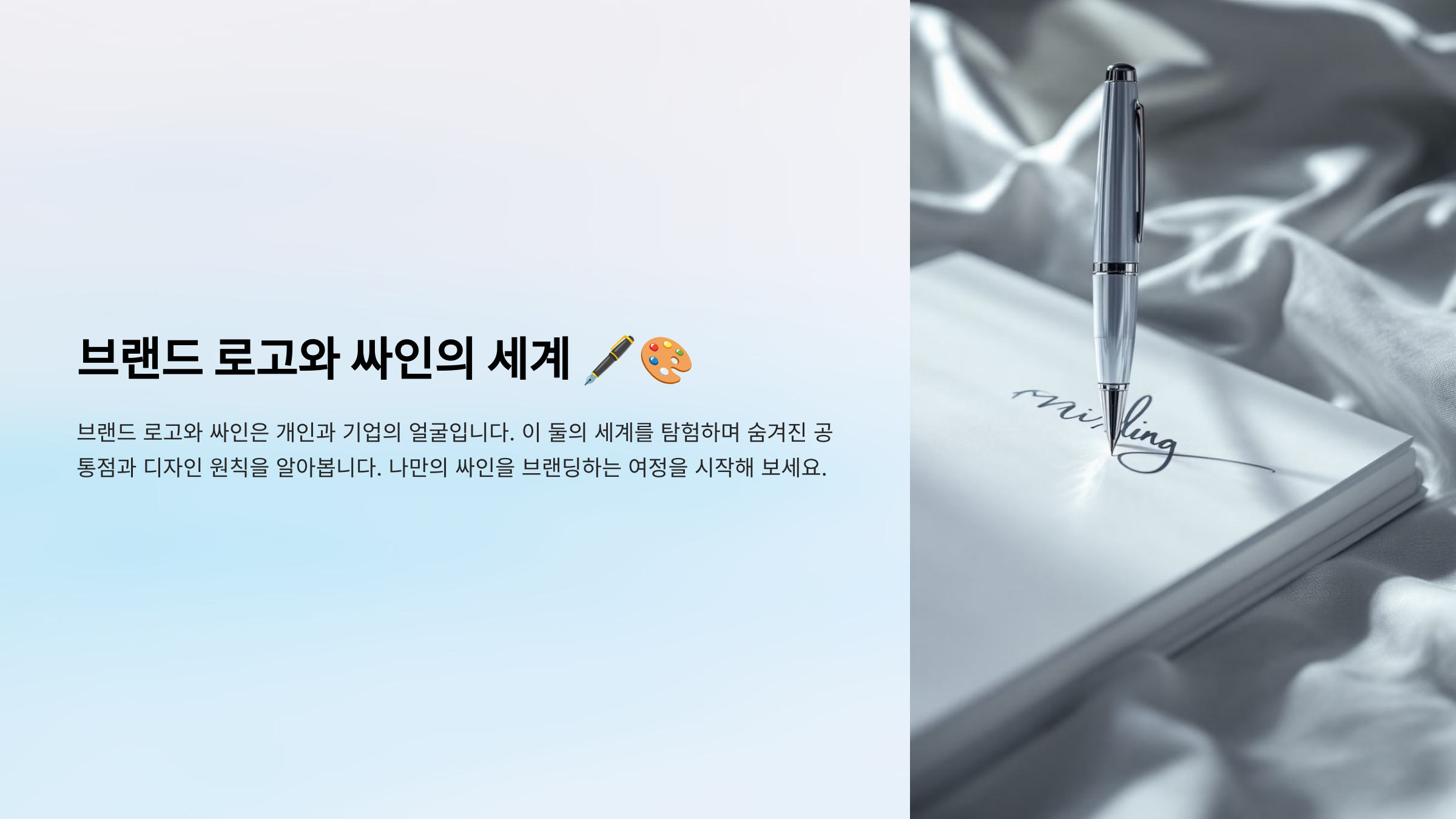
싸인과 브랜드 로고는 단순한 글자가 아니라 강한 인상을 남기는 디자인 요소예요. 브랜드 로고가 회사의 정체성을 나타내듯, 싸인도 자신만의 개성을 드러내는 중요한 요소랍니다! ✍🔥
🔹 브랜드 로고와 싸인의 공통점
✔ 한 번 보면 기억에 남아야 한다
✔ 너무 복잡하지 않고 간결해야 한다
✔ 디자인의 흐름과 균형이 중요하다
✔ 개성을 반영해야 브랜드(싸인)의 차별성이 생긴다.
📌 브랜드 로고 & 싸인의 유사점 ✨
비교 요소 브랜드 로고 개인 싸인 기억에 남는 디자인 아이콘이나 심볼을 사용해 인상적인 로고 제작 이니셜 강조 또는 독특한 필기체 활용 간결함 불필요한 장식을 줄이고 단순한 형태 유지 빠르게 쓸 수 있도록 복잡한 요소 제거 개성 표현 브랜드의 정체성을 색상과 폰트로 표현 이름의 특성을 살려 개성 있게 디자인 균형과 흐름 로고의 크기와 간격을 정리해 균형 유지 획의 연결과 마무리를 부드럽게 조정 이제 심플하지만 강렬한 브랜드 로고의 특징을 살펴볼까요? 🔥
심플하지만 강렬한 브랜드 로고 특징 🔥
유명 브랜드의 로고를 보면 단순하면서도 강한 인상을 남기는 특징이 있어요. 싸인도 마찬가지로 불필요한 요소를 줄이고, 기억에 남는 디자인을 만들어야 해요. ✍🔥
🔹 강렬한 브랜드 로고의 특징
✔ 단순한 디자인 – 복잡한 요소 없이 깔끔한 형태
✔ 한눈에 알아볼 수 있는 구조 – 직관적인 스타일
✔ 균형 잡힌 비율 – 너무 길거나 짧지 않게 조정
✔ 특징적인 포인트가 있음 – 로고만 보고도 브랜드를 떠올릴 수 있음
📌 유명 브랜드 로고에서 배우는 핵심 ✨
브랜드 로고 특징 싸인에 적용 가능? Nike 곡선의 스우시(swoosh) 심볼, 빠르고 역동적인 느낌 싸인의 끝을 부드러운 곡선으로 마무리 Coca-Cola 부드러운 필기체 스타일, 유려한 곡선 싸인을 필기체로 자연스럽게 연결 Apple 심플한 아이콘, 불필요한 요소 없음 싸인을 최소한의 획으로 구성 Google 밝고 친근한 색상, 명확한 가독성 싸인을 명확하고 직관적으로 디자인 이제 유명 브랜드에서 배우는 싸인 디자인 원칙을 알아볼까요? ✅
유명 브랜드에서 배우는 싸인 디자인 원칙 ✅
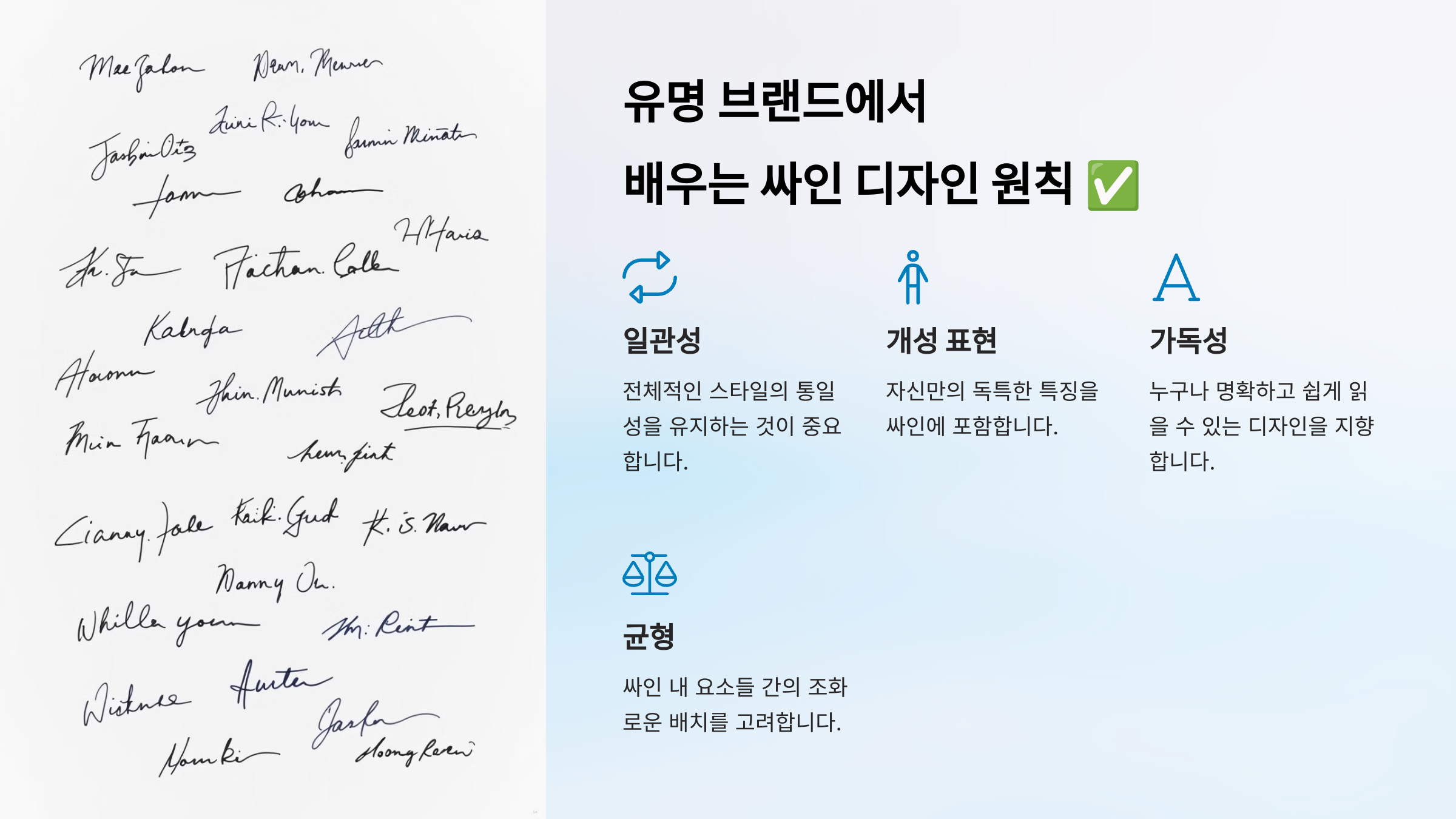
브랜드 로고처럼 싸인도 단순하면서도 강렬한 인상을 남겨야 해요. 유명 브랜드의 디자인 원칙을 참고하면 더욱 세련되고 기억에 남는 싸인을 만들 수 있어요! ✍🔥
🔹 싸인 디자인 원칙 4가지
✔ 미니멀리즘 – 불필요한 요소를 제거하고 핵심만 남기기
✔ 균형과 조화 – 글자의 크기와 간격을 조정해 안정감 있는 디자인 만들기
✔ 흐름과 속도 – 자연스럽게 이어지는 획을 활용해 부드러운 스타일 완성
✔ 차별화된 개성 – 이니셜, 곡선, 밑줄 등 자신만의 특징을 추가
📌 싸인 디자인 원칙 4가지 ✨
원칙 설명 예시 미니멀리즘 복잡한 장식을 줄이고 심플한 스타일 유지 Apple 로고처럼 간결한 싸인 균형과 조화 글자의 크기, 간격, 기울기를 맞춰 정돈된 디자인 Google 로고처럼 가독성이 좋은 싸인 흐름과 속도 자연스럽게 이어지는 획으로 부드러운 필기체 구성 Coca-Cola 로고처럼 유려한 곡선 활용 차별화된 개성 이니셜, 독특한 기호, 밑줄 등을 활용해 브랜드화 Nike 로고처럼 독창적인 포인트 추가 이제 브랜드 로고에서 따온 싸인 스타일 예시를 살펴볼까요? ✍
브랜드 로고에서 따온 싸인 스타일 예시 ✍
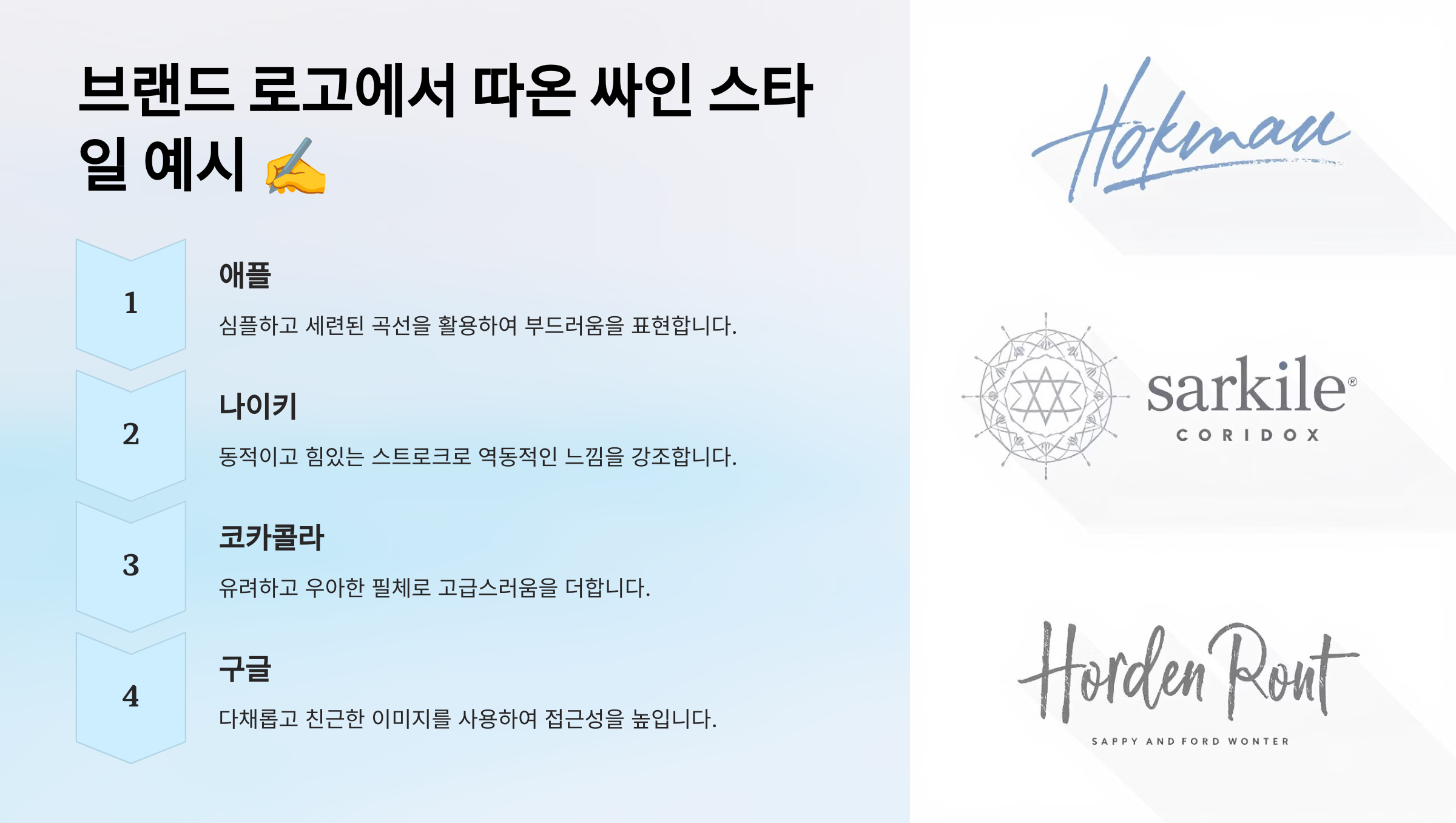
유명 브랜드의 로고를 참고하면 더 세련되고 강렬한 싸인을 만들 수 있어요. 각 브랜드가 가지고 있는 디자인 원리를 싸인에 적용하면 독창적인 스타일을 완성할 수 있답니다! ✍🔥
🔹 브랜드에서 영감 얻은 싸인 스타일
✔ Nike 스타일 – 곡선을 활용한 빠르고 유려한 흐름
✔ Coca-Cola 스타일 – 필기체를 부드럽게 연결해 감각적인 느낌
✔ Apple 스타일 – 군더더기 없이 심플한 디자인
✔ Lacoste 스타일 – 이니셜과 작은 심볼을 활용한 개성적인 스타일
📌 브랜드 로고 기반 싸인 스타일 예시 ✨
브랜드 스타일 싸인 적용 방식 특징 Nike 곡선을 강조하여 역동적인 느낌 부드러운 흐름, 빠른 필기 가능 Coca-Cola 필기체를 활용해 자연스럽게 연결 우아하고 감각적인 스타일 Apple 불필요한 요소 없이 간결하게 구성 미니멀하면서도 세련된 느낌 Lacoste 이니셜과 작은 기호를 조합 독창적인 포인트 추가 가능 이제 싸인에 적용할 수 있는 디자인 요소를 살펴볼까요? 🎯
싸인에 적용할 수 있는 디자인 요소 🎯
싸인을 더욱 세련되게 만들려면 디자인 요소를 적절히 활용하는 것이 중요해요. 단순한 글씨를 넘어, 브랜드 로고처럼 시각적으로도 매력적인 스타일을 만들어야 해요! ✍🔥
🔹 싸인에 활용할 수 있는 디자인 요소
✔ 곡선과 직선 조화 – 부드러운 흐름을 살리거나 강한 인상을 주는 요소
✔ 이니셜 강조 – 싸인의 첫 글자를 키우거나 특이한 획 추가
✔ 밑줄 및 기호 추가 – 별⭐, 점•, 스마일😊 등 개성 있는 포인트
✔ 대문자 & 소문자 조합 – 글자 크기 변화를 통해 스타일 살리기
📌 싸인 디자인에 활용할 요소 ✨
디자인 요소 설명 활용 예시 곡선과 직선 조화 부드러운 곡선과 강한 직선 조합으로 인상적 디자인 Nike 스타일의 유려한 흐름 이니셜 강조 첫 글자를 키우거나 특이한 획 추가 Tesla CEO 엘론 머스크 스타일 밑줄 및 기호 추가 밑줄, 점, 작은 기호 등을 활용해 개성 표현 Lacoste 로고처럼 작은 기호 활용 대문자 & 소문자 조합 글자의 크기를 변형해 스타일 연출 Coca-Cola의 필기체 조합 이제 브랜드처럼 나만의 싸인 브랜딩하는 법을 알아볼까요? 💼
브랜드처럼 나만의 싸인 브랜딩하기 💼
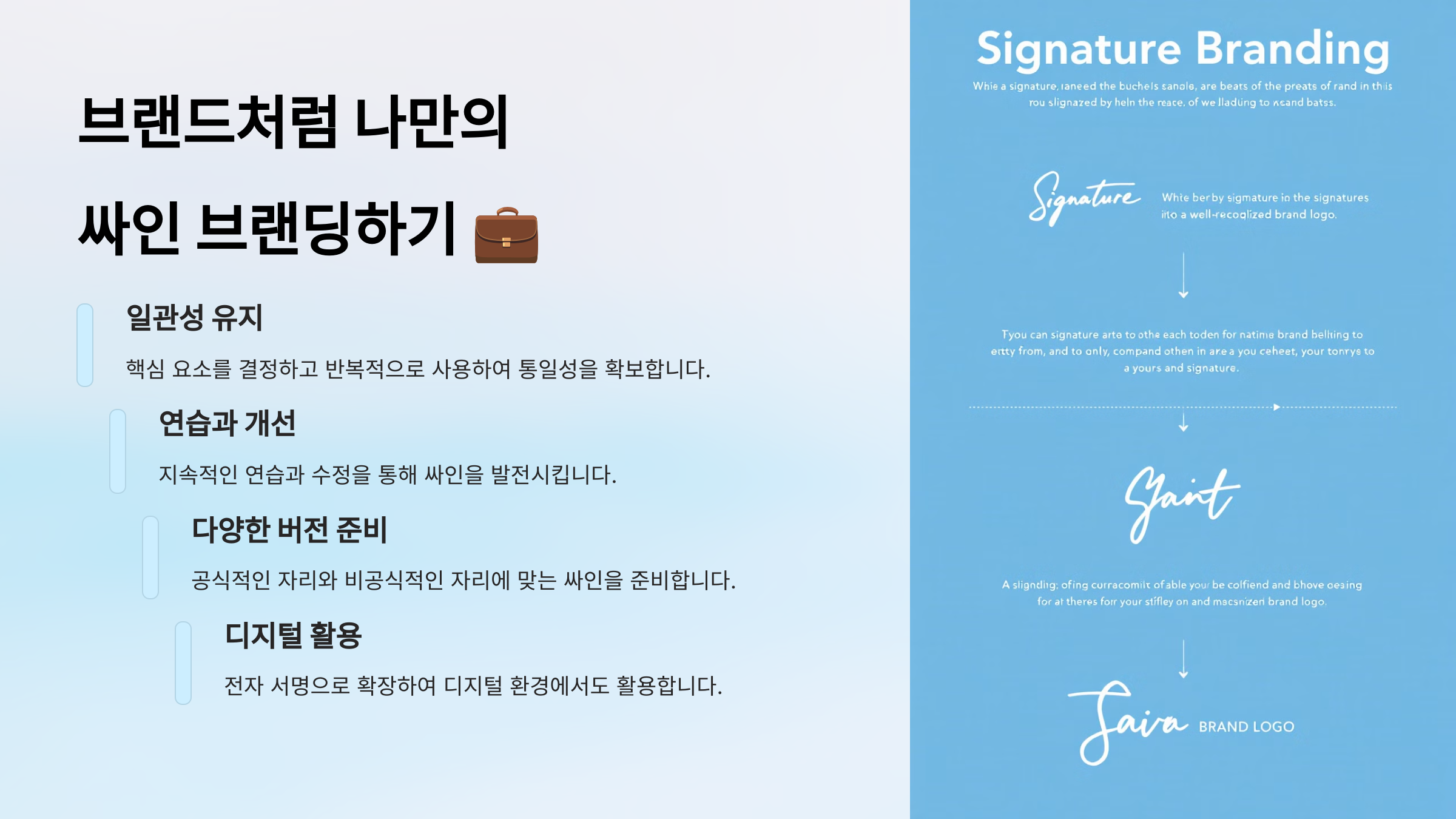
싸인은 단순한 서명이 아니라 자신을 대표하는 브랜드와 같은 역할을 해요. 유명 브랜드가 로고를 통해 정체성을 표현하듯, 나만의 싸인을 브랜드화할 수 있어요! ✍🔥
🔹 싸인을 브랜드처럼 만들기 위한 팁
✔ 일관된 스타일 유지 – 언제 어디서든 동일한 형태로 싸인
✔ 특징적인 포인트 추가 – 이니셜, 곡선, 기호 등 개성 살리기
✔ 디지털과 아날로그 모두 활용 – 전자 서명, 명함, 문서 등에 동일하게 적용
✔ 반복 연습을 통해 자연스럽게 만들기
📌 싸인을 브랜드처럼 활용하는 법 ✨
브랜딩 요소 설명 활용 예시 일관된 스타일 항상 동일한 싸인을 유지해 신뢰감 형성 공식 문서, 명함, 계약서 활용 특징적인 포인트 싸인에 개성을 담아 인상 깊게 만들기 이니셜 강조, 곡선 추가, 기호 활용 디지털 & 아날로그 적용 종이 서명뿐만 아니라 디지털 서명까지 활용 전자 문서 서명, SNS 프로필 활용 반복 연습 꾸준한 연습으로 자연스럽게 정착 하루 10번 이상 연습 이제 싸인에 대한 궁금증을 해결할 시간! FAQ에서 자주 묻는 질문을 정리해 볼까요? ❓
FAQ ❓
Q1. 싸인을 브랜드처럼 만들려면 가장 중요한 요소는 무엇인가요?
A1. 싸인을 브랜드처럼 만들려면 일관된 스타일과 개성 있는 디자인이 중요해요. ✔ 언제 어디서든 동일한 싸인 유지 ✔ 이니셜, 곡선, 밑줄 등 특징적인 포인트 추가 ✔ 디지털과 아날로그에서 모두 활용 가능해야 함
Q2. 싸인을 만들 때 가장 피해야 할 실수는?
A2. 싸인을 만들 때 피해야 할 실수는 다음과 같아요. ✔ 너무 복잡한 디자인 – 싸인을 빠르게 작성할 수 없게 만듦 ✔ 일관되지 않은 스타일 – 싸인을 쓸 때마다 달라지면 신뢰감 저하 ✔ 가독성이 떨어지는 디자인 – 남들이 읽기 어렵다면 효과 감소
Q3. 싸인을 바꿔도 괜찮을까요?
A3. 개인적인 싸인은 언제든 바꿀 수 있지만, 공식 문서에서는 신중해야 해요. ✔ 은행, 공공기관 등에 등록된 싸인은 변경이 필요할 수도 있음 ✔ 새로운 싸인을 정착시키기 위해 꾸준한 연습이 필수
Q4. 싸인에 기호(⭐, ✔, 💫)를 추가해도 될까요?
A4. 기호를 활용하면 싸인에 개성을 더할 수 있어요. ✔ 별(⭐), 밑줄(━), 점(•) 등을 추가해 독창적인 스타일 연출 ✔ 너무 많은 장식은 싸인을 복잡하게 만들 수 있으니 적절한 선에서 활용
Q5. 디지털 문서와 종이 문서에서 같은 싸인을 쓰는 것이 좋을까요?
A5. 디지털과 종이 문서에서 동일한 싸인을 유지하는 것이 좋아요. ✔ 태블릿, 스타일러스 펜을 이용해 자연스러운 디지털 서명 연습 ✔ Adobe Sign, DocuSign 같은 전자 서명 도구 활용
Q6. 싸인 크기는 어떻게 조절해야 하나요?
A6. 싸인 크기는 상황에 맞게 조절해야 해요. ✔ 공식 서류에서는 작은 크기로 깔끔하게 ✔ 팬 사인회, 명판 등에서는 크게 써서 강한 인상 남기기
Q7. 싸인을 연습할 때 효과적인 방법이 있나요?
A7. 싸인을 자연스럽게 만들려면 반복 연습이 필요해요. ✔ 매일 5~10분씩 싸인 연습하기 ✔ 다양한 크기로 써보며 균형감 익히기 ✔ 빠르게 작성하는 연습을 통해 흐름 만들기
Q8. 유명인의 싸인을 참고해도 괜찮을까요?
A8. 네! 유명인의 싸인을 참고하면 효율적이면서도 멋진 싸인을 만드는 데 도움이 돼요. 하지만 완전히 똑같이 따라 하기보다는, 자신의 스타일을 반영하여 변형하는 것이 중요해요. 🎨
이제 싸인을 브랜드처럼 활용하는 방법까지 완벽하게 배웠어요! 🎯 연습을 통해 자신만의 멋진 싸인을 완성하고, 공식 문서뿐만 아니라 디지털 환경에서도 적극 활용해 보세요! ✍🔥